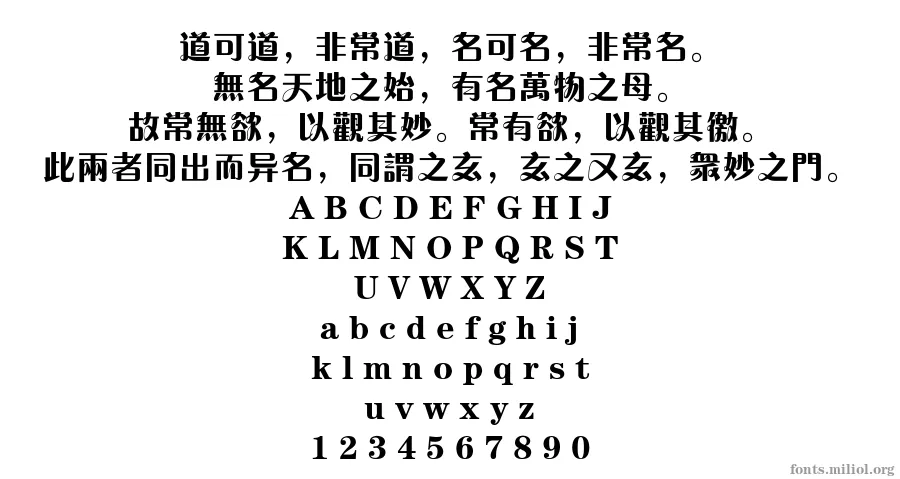
《方正粗活意繁体:传统与现代交融的字体艺术》
方正粗活意繁体(FZCuHuoYi-M25T)是一款兼具传统书法韵味与现代设计美学的繁体字库。其笔触浑厚有力,转折处保留毛笔书写的自然顿挫,横竖间透露出金石篆刻的刚劲气质,特别适合需要展现文化厚重感的视觉设计。字体名称中的"活意"二字,恰如其分地体现了它在规范字形中融入的动态美感——既有印刷体的工整,又不失手写体的灵动。
这款字体的设计团队深入研究宋代刻本与明清匾额书法,将历史感融入数字化设计。笔画末端微微上扬的燕尾处理,既传承了隶书的古朴特征,又通过标准化制式保证了多字号环境下的清晰度。其GB1-0编码版本严格遵循中文编码规范,确保在各类数字化场景中稳定显示。
在应用层面,方正粗活意繁体特别适合文化类海报、书籍装帧、品牌标识等场景。当用于茶文化、非遗传承等主题设计时,能瞬间唤起观者对传统的共鸣;而搭配简约的版式设计时,又能形成古今对话的视觉张力。这款字体不仅是工具,更是连接汉字美学过去与未来的桥梁。